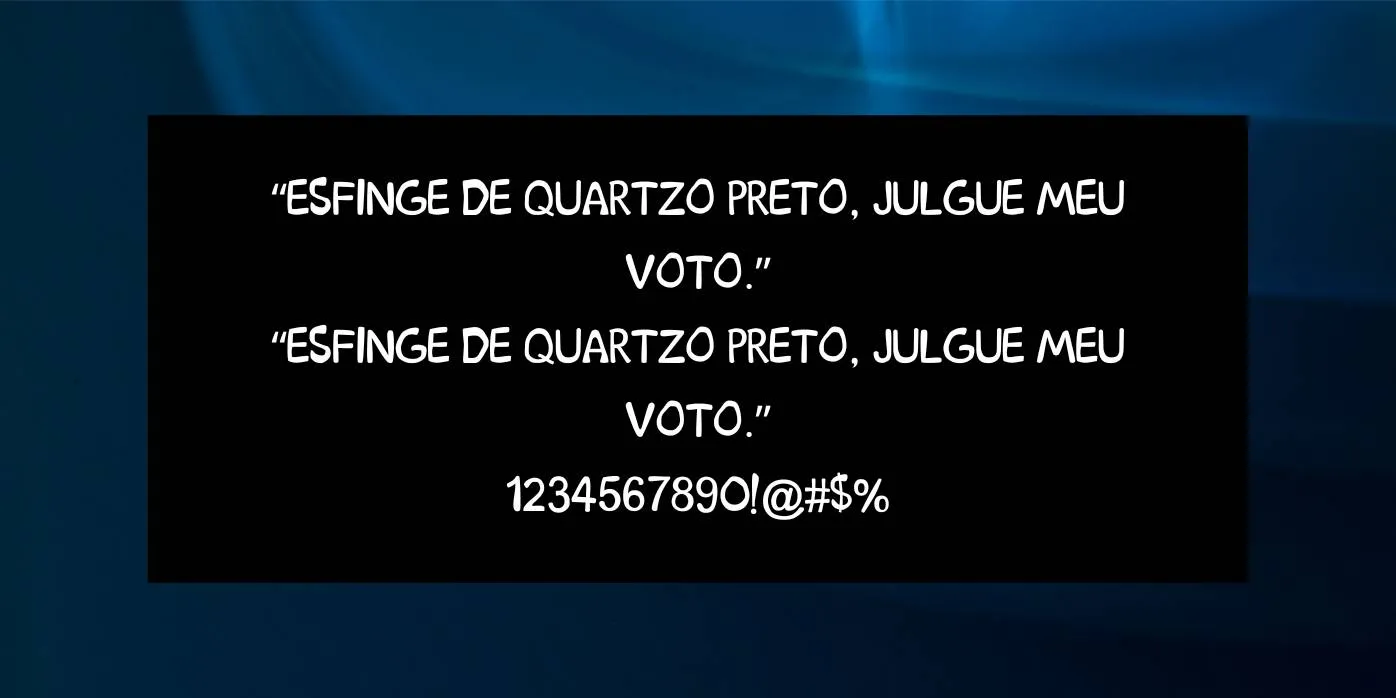
Fonte Scooby Doo é uma fonte moderna inspirada na icônica animação de mesmo nome. Foi criado pela designer de tipos da Monotype Imaging, Lauren Ashpole. A fonte é classificada como uma fonte decorativa e é frequentemente usada em designs divertidos e infantis.
Esta fonte impressionante tem um estilo único e reconhecível, com letras arredondadas e bordas ligeiramente irregulares. Inclui caracteres em casos e causas, bem como números e símbolos comuns.
Além disso, essa fonte também oferece uma variedade de recursos adicionais, como pesos e estilos diferentes, incluindo negrito, itálico e sublinhado.
Uso da Scooby Doo
Esta incrível fonte pode ser usada em vários contextos na língua portuguesa. Uma das aplicações mais comuns é no design gráfico e na publicidade, principalmente em materiais voltados para o público infantil. A fonte pode ser usada em pôsteres, banners, convites e outros materiais promocionais, criando um visual divertido e cativante.
Além disso, essa fonte também pode ser utilizada em produtos relacionados à franquia Scooby Doo, como camisetas, brinquedos e acessórios. Nesse caso, a fonte ajuda a criar uma identidade visual consistente com a marca e torna os produtos mais atraentes para os fãs. Essa tipografia é adequada para Adobe e Canva.
Outra aplicação interessante dessa tipografia é em jogos eletrônicos e aplicativos para dispositivos móveis. A fonte pode ser utilizada em menus, títulos, diálogos e outros elementos da interface, ajudando a criar um ambiente lúdico e descontraído.
| Designer | Lauren Ashpole |
| Estilo | Chique |
Qual é o tipo de fonte Scooby Doo?
Esta tremenda fonte é classificada como uma fonte decorativa extravagante.
Onde podemos usar a fonte Scooby Doo?
Essa fonte pode ser utilizada em diversos contextos, desde design gráfico e publicidade até jogos eletrônicos e materiais educativos. É especialmente indicado para materiais destinados ao público infantil e ajuda a criar um ambiente lúdico e descontraído.